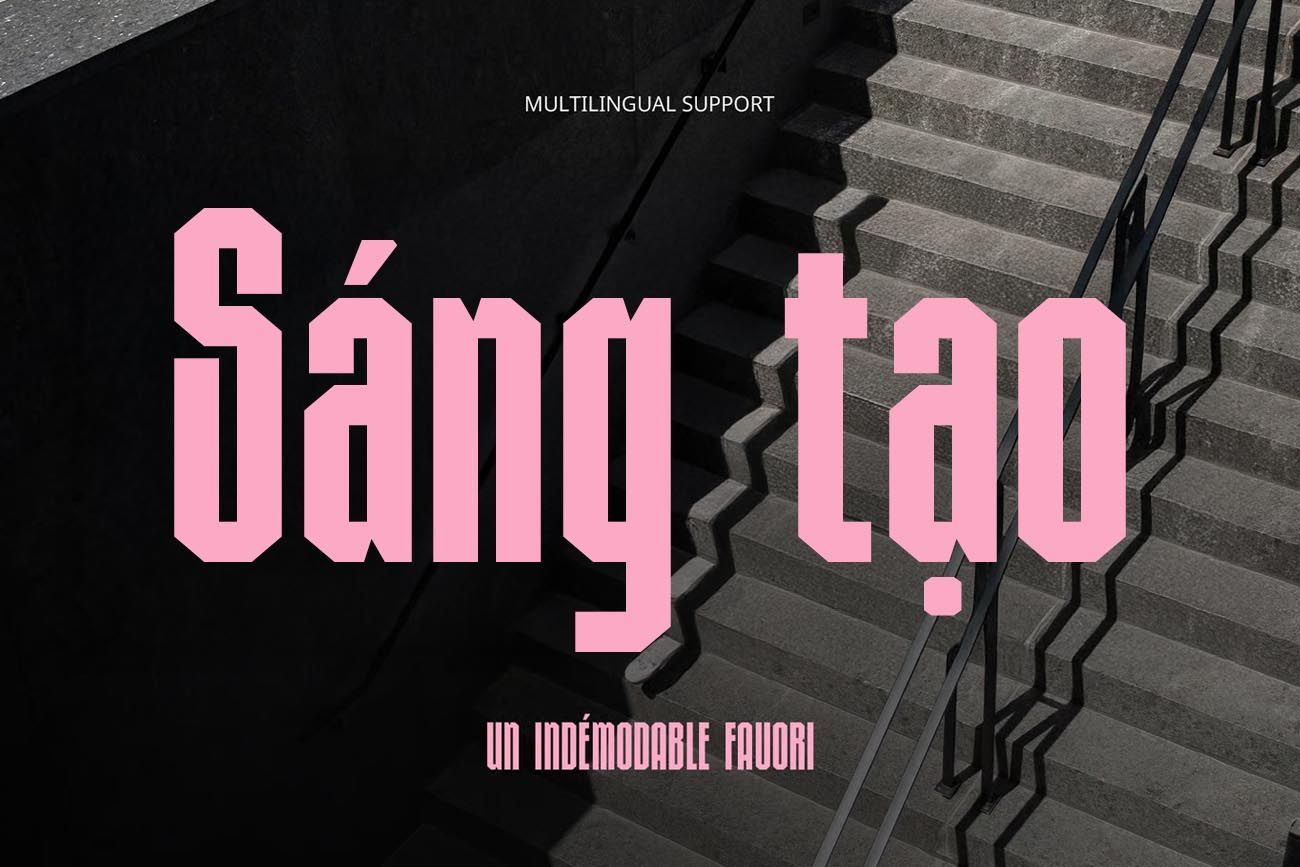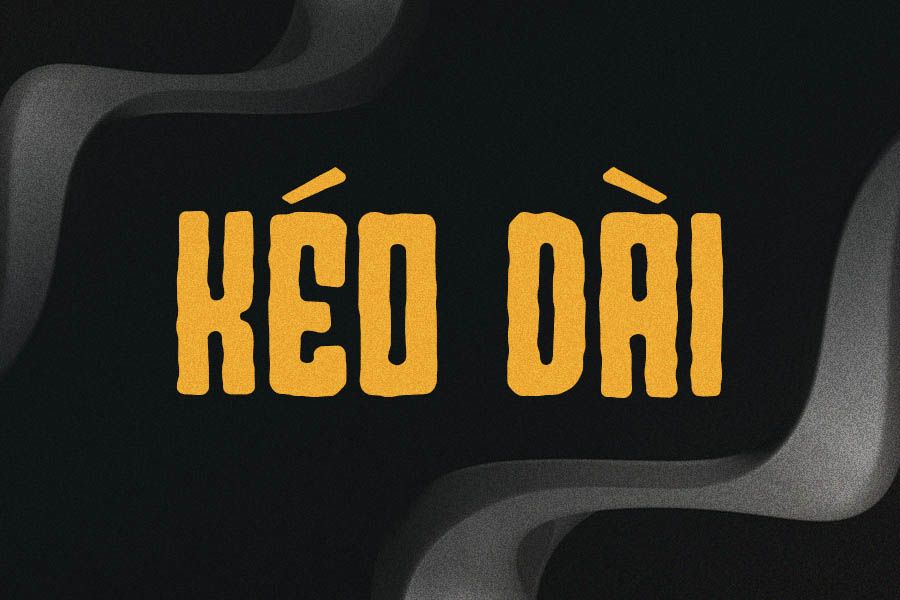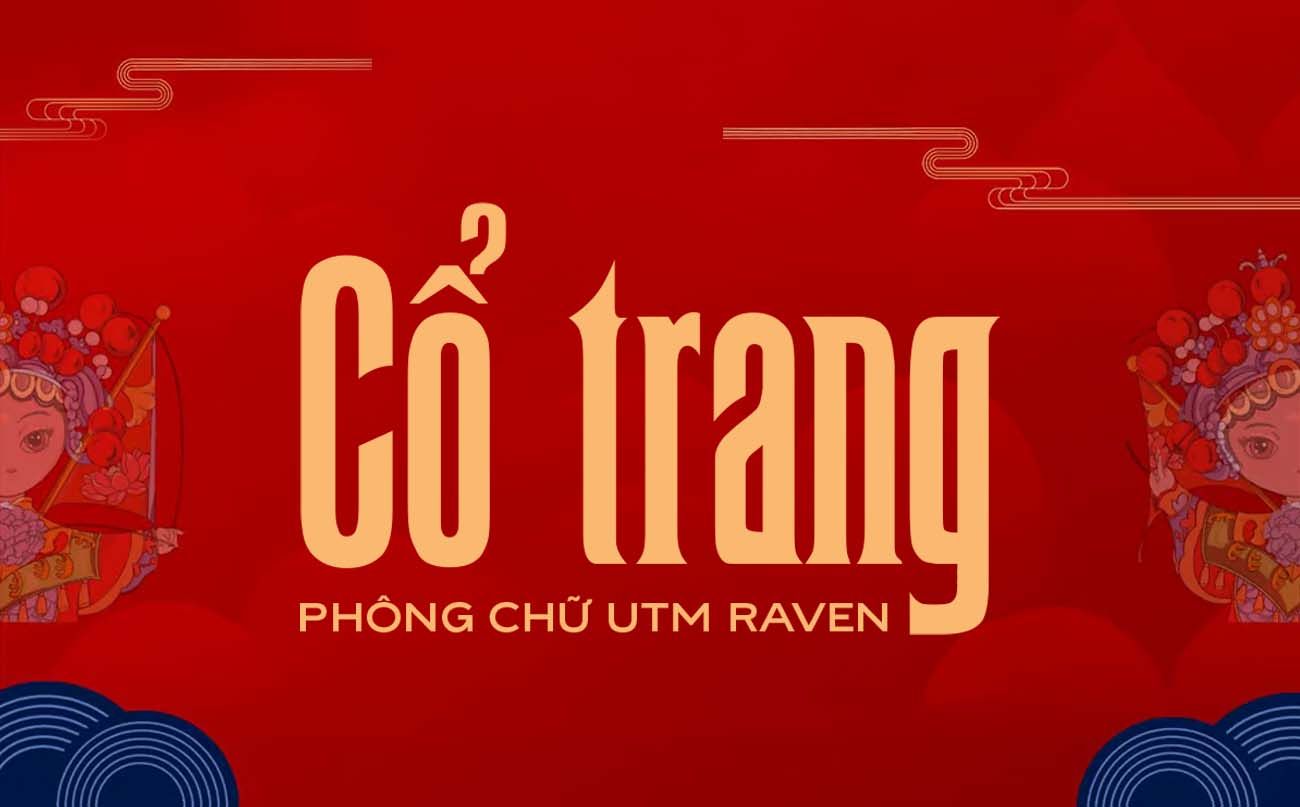
TOP 10+ font chữ kéo dài Việt hóa độc lạ nhất 2025
Trong thế giới thiết kế hiện đại, kiểu chữ không chỉ là công cụ truyền tải thông điệp mà còn là yếu tố tạo nên cá tính và sự khác biệt cho sản phẩm sáng tạo. Nếu bạn đang tìm kiếm một lựa chọn vừa độc đáo, vừa dễ sử dụng, chắc chắn không thể bỏ qua font chữ kéo dài – dòng font mang lại cảm giác tinh tế, sang trọng và đầy sáng tạo. Trong bài viết này, chúng ta sẽ cùng khám phá 10 font chữ kéo dài ấn tượng, giúp bạn nâng tầm mọi dự án thiết kế từ poster, banner, logo cho đến ấn phẩm nghệ thuật.
Vì sao nên sử dụng font chữ kéo dài?
Font chữ kéo dài thường có cấu trúc thanh mảnh nhưng tinh tế, các ký tự được kéo dãn cân đối, tạo nên sự hiện đại và tối giản. Một số lý do khiến dòng font này ngày càng được yêu thích:
Tính thẩm mỹ cao: Dáng chữ dài, gọn giúp tác phẩm mang hơi thở thời thượng, phù hợp với các thiết kế cao cấp.
Dễ gây ấn tượng: Font chữ kéo dài nổi bật trong các tiêu đề, poster quảng cáo, bao bì sản phẩm.
Đa dạng ứng dụng: Có thể kết hợp cùng font serif, sans-serif hoặc handwritten để tạo điểm nhấn.
Phù hợp nhiều lĩnh vực: Từ thời trang, mỹ phẩm, nội thất, đến sự kiện, truyền thông, font chữ kéo dài đều phát huy hiệu quả.
Dưới đây là danh sách 10 font chữ kéo dài mà bạn có thể áp dụng cho các dự án thiết kế khác nhau. Mỗi font đều có đặc điểm riêng, dễ tải và dễ cài đặt, phù hợp từ người mới đến designer chuyên nghiệp.
1. Font chữ thể thao mạnh mẽ và cá tính TH Astrophel Việt hóa
Mô tả: Bạn đang tìm kiếm một font chữ mạnh mẽ, hiện đại và đầy cá tính? TH Astrophel là lựa chọn lý tưởng. Font chữ condensed sans-serif này nổi bật với các đường nét sắc sảo, vuông vức, thể hiện sự chuyên nghiệp, bản lĩnh và tốc độ trong từng ký tự. Phiên bản Việt hóa giữ nguyên tinh thần thiết kế gốc, phù hợp cho poster, banner hay các dự án cần sự dứt khoát, vận động và phong cách thể thao năng động.
2. Font cổ trang cứng cáp mang dáng dấp cung đình xưa UTM Raven
Mô tả: UTM Raven là font serif cứng cáp, uy nghiêm, kết hợp nét thư pháp phương Tây với hơi thở Á Đông, tái hiện dáng chữ triều đình xưa. Với các đường cong sắc sảo, móc dài và nhọn, font mang cảm giác quyền lực và nghiêm trang. UTM Raven  phù hợp cho thiết kế cung đình, tranh cổ phong, poster phim cổ trang hoặc game kiếm hiệp, tôn vinh yếu tố văn hóa và truyền thống.
3. Font chữ công nghệ mạnh mẽ và hiện đại TH Lugak Sans Việt hóa
Mô tả: TH Lugak Sans là font chữ Sans Serif hiện đại, thiết kế hình học, tối giản nhưng mạnh mẽ, tạo cảm giác vững chắc, gãy gọn, lý tưởng cho các dự án công nghệ, kỹ thuật số và truyền thông.
4. Font chữ cứng cáp mạnh mẽ TH Cungcap 7 Việt hóa
Mô tả: TH Cungcap 7 sở hữu phong cách mạnh mẽ, hiện đại và chắc chắn, với các nét chữ vuông vức, góc cạnh rõ ràng, tạo cảm giác vững chãi và đáng tin cậy. Đây là kiểu sans-serif, toàn bộ chữ in hoa đồng đều, mang đến vẻ trang nhã, chuyên nghiệp và thu hút sự chú ý.
5. Font chữ chủ đề lịch sử TH Lichsu 3 Việt hóa
Mô tả: TH Lichsu 3 mang đậm hơi thở lịch sử với kiểu dáng trang nghiêm, uyển chuyển, phù hợp cho các thiết kế mang chủ đề Phật giáo. Các nét chữ mềm mại nhưng vẫn rõ ràng, tạo cảm giác truyền thống và trang trọng. Font được Việt hóa đầy đủ, dễ dàng áp dụng cho poster, banner, ấn phẩm giáo dục hoặc các dự án liên quan đến văn hóa và đạo Phật, mang lại sự tinh tế và hài hòa cho thiết kế.
Tác giả gốc: Đang update
Tác giả Việt hóa: Admin S99.vn
6. Font chữ cổ điển TH Hustle Culture Việt hóa
Mô tả: TH Hustle Culture là một font cổ điển với các đường cong uốn lượn tinh tế tạo nên tổng thể độc đáo, phù hợp cho logo, ấn phẩm truyền thông hay bao bì nhãn mác. Bộ font này không chỉ mang vẻ cổ điển mà còn cung cấp nhiều ký tự bổ sung, giúp người dùng thay thế linh hoạt.
Tác giả gốc: Hendry
Tác giả Việt hóa: Admin S99.vn
7. Font chữ cứng hiện đại VL Monologue Việt hóa
Mô tả: VL Monologue sở hữu những đường nét góc cạnh, cứng cáp, mang đến ấn tượng mạnh mẽ, thể hiện sự quyết đoán và chuyên nghiệp. Thiết kế hiện đại của font phù hợp với nhiều loại hình sáng tạo như logo, poster, banner, đặc biệt là các ấn phẩm về công nghệ, thể thao hay sản phẩm dành cho nam giới.
8. Font chữ không chân TH Tokyo Việt hóa
Mô tả: TH Tokyo thuộc kiểu sans serif hiện đại, không chân, với các nét thanh mảnh nhưng rõ ràng, mang đến cảm giác tinh tế, gọn gàng và chuyên nghiệp. Font này có thiết kế chữ tối giản, dễ đọc, phù hợp cho tiêu đề, logo, ấn phẩm quảng cáo hay giao diện số.